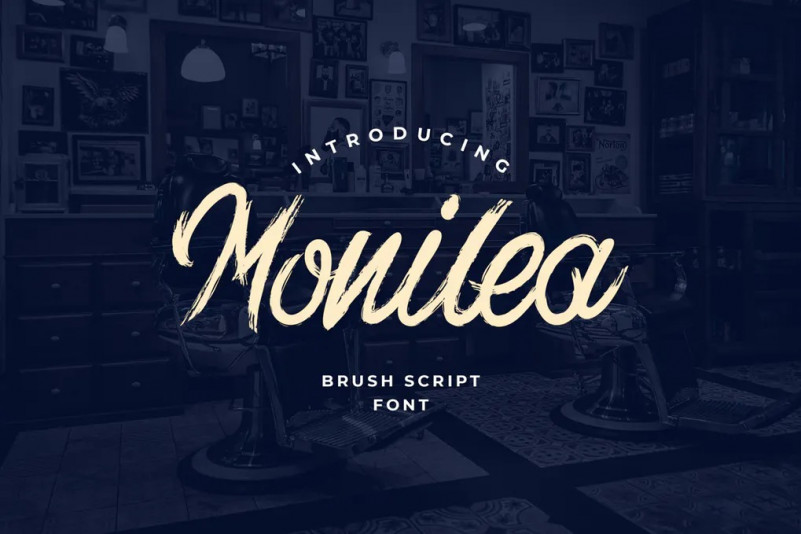
Monilea Font
Monilea est parfait pinceau script manuscrit pour les projets de marque, Logo, conceptions de mariage, messages de médias sociaux, publicités, emballage de produits, conceptions de produits, étiquette, photographie, filigrane, invitation, papeterie et tous les projets qui ont besoin de goût de l’écriture manuscrite.
Cette police a un flux vraiment agréable donc vous l’utilisez dans un grand texte si vous voulez leur donner une touche de personnalité. Il peut être utilisé sur le contenu des médias sociaux, pour l’image de marque ou l’emballage.